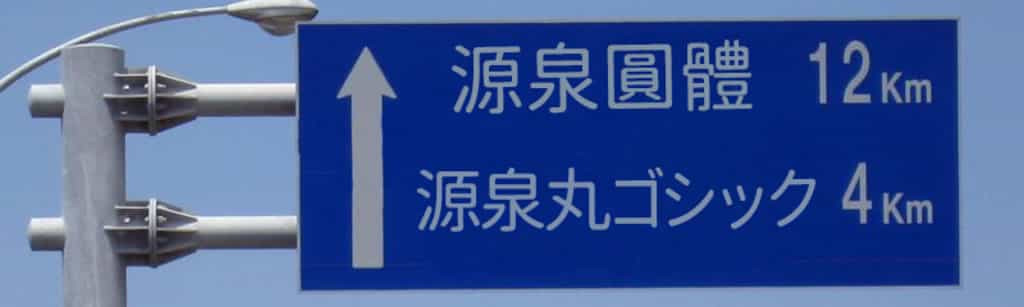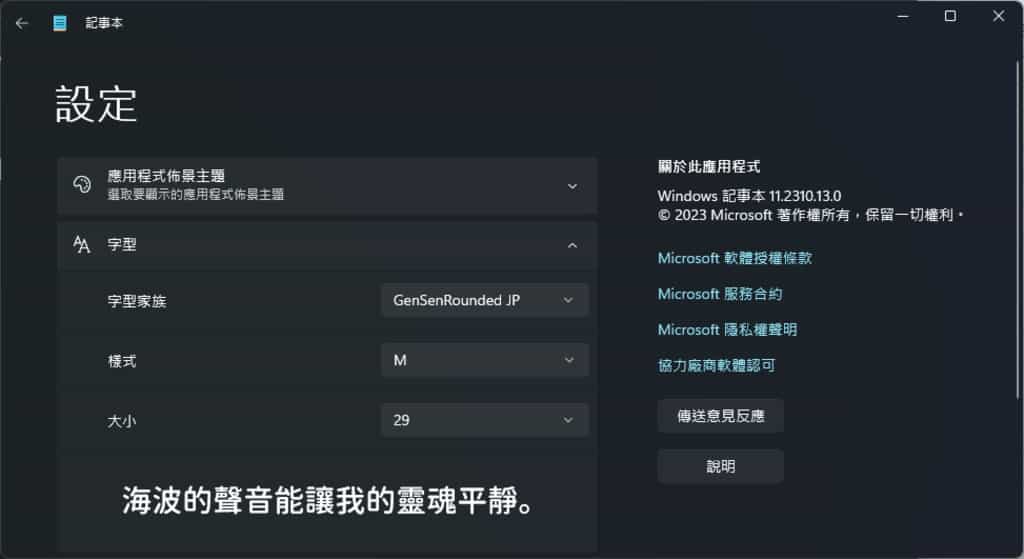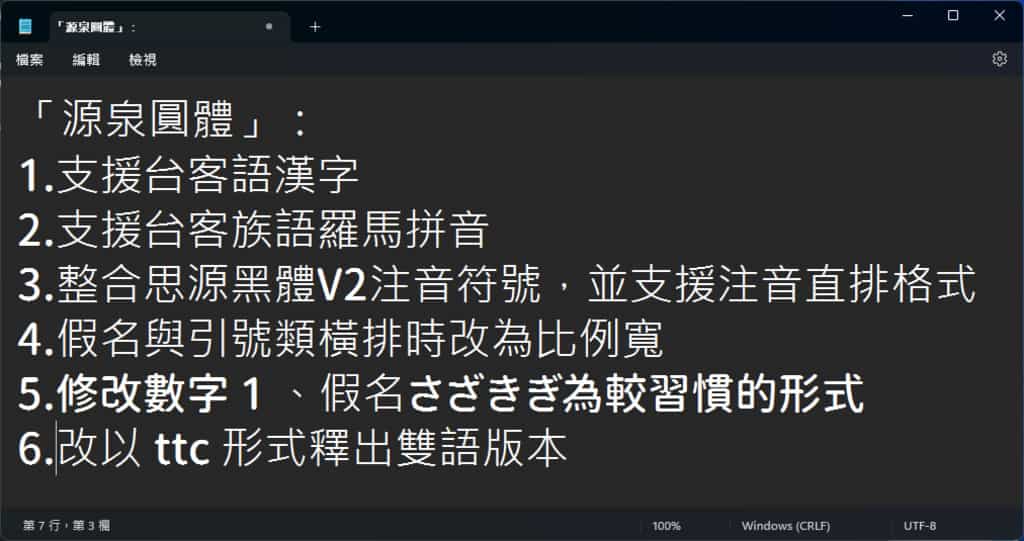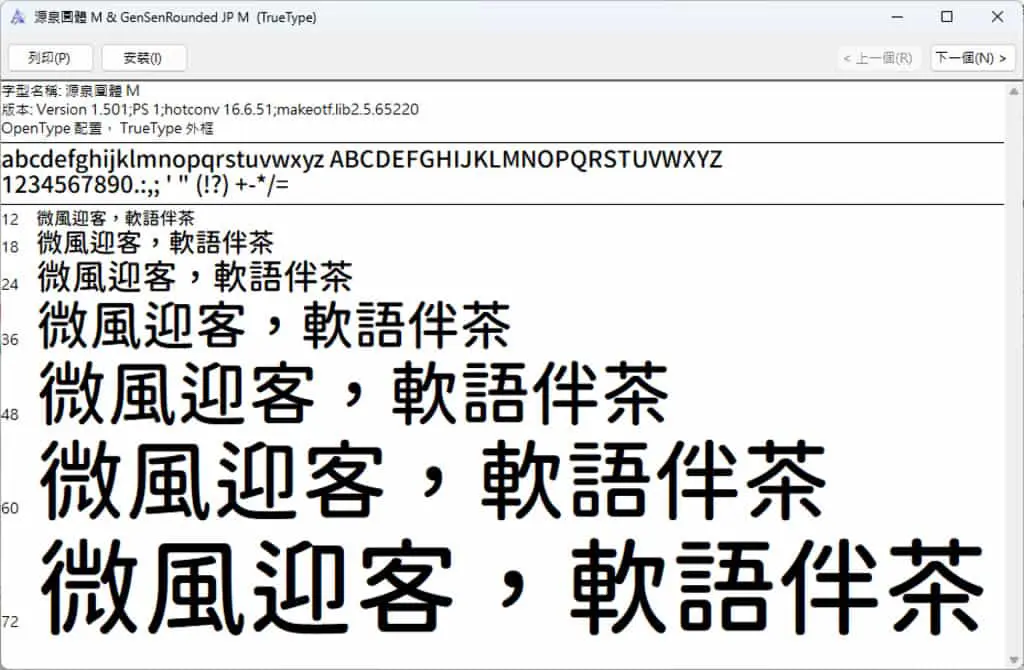
「源泉圓體」是源於思源黑體的開放原始碼中文字型。根據作者的自述,就是把筆畫全改圓,將黑體的腳盡可能拔除,並加上封閉區域的內圓角處理,盡可能去逼近圓體樣貌,整體看起來會比一般的圓體看起來更為工整與方正。「源泉圓體」以開放原始碼的形式在 GitHub 平台上提供,供有需要的使用者免費下載。源泉圓體的特點在於涵蓋了幾乎所有常見的字元,同時支援繁體中文和日文。不論使用的是 Windows 或 Mac 作業系統,都可以輕鬆地進行下載和安裝。此外,在授權上亦基於 SIL Open Font License 1.1 授權條款公開發布,所以可自由使用,不限個人或商業用途。